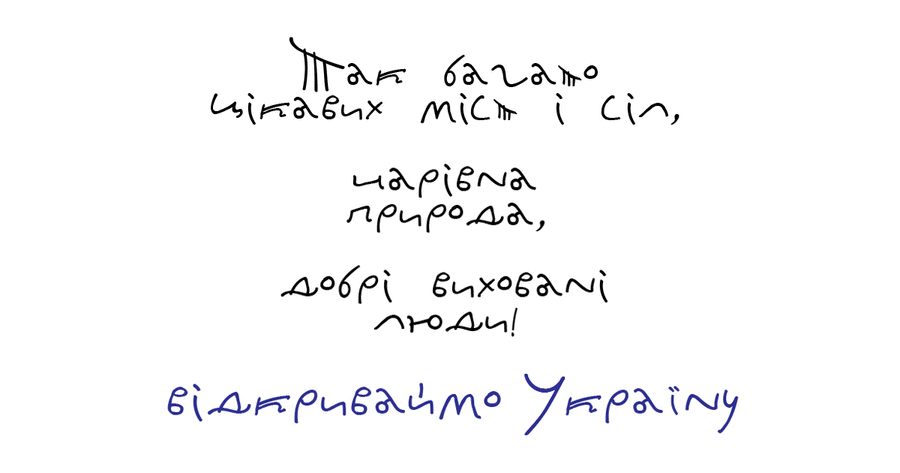
Шрифт Kudriavchenko розроблений спеціально для українських текстів, але латинка в ньому також є. Це веселий і позитивний шрифт, який відносить нас до часів Київської Русі, нагадуючи старовинні графіті на стінах храмів. Основним натхненням слугував почерк українського художника Олександра Кудрявченко, яким оформлено більшість його робіт. Шрифт розробила Ірина Кудрявченко у 2019 році.